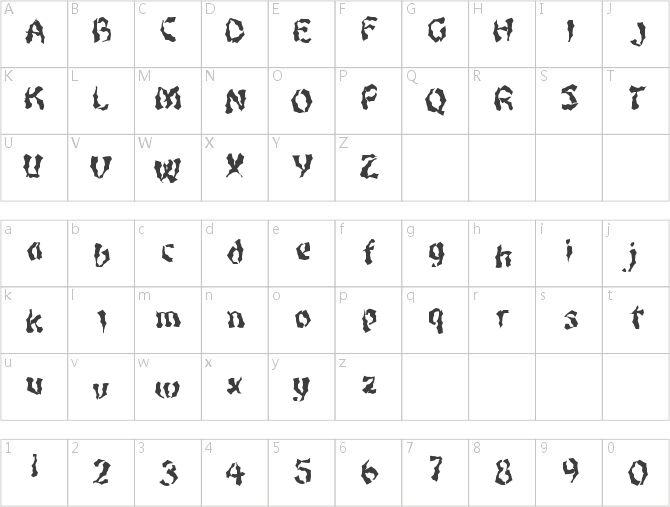
FZ WACKY 47
FZ WACKY 47介紹
FZ WACKY 47字體字庫(kù)是一款讓人賞心悅目、百看不厭的英文字體,適合各類(lèi)廣告和產(chǎn)品包裝設(shè)計(jì)應(yīng)用,字體大小0.07MB,格式為ttf字體,上傳用戶(hù)是快霸中國(guó),作者/版權(quán)方為未知
FZ WACKY 47效果圖